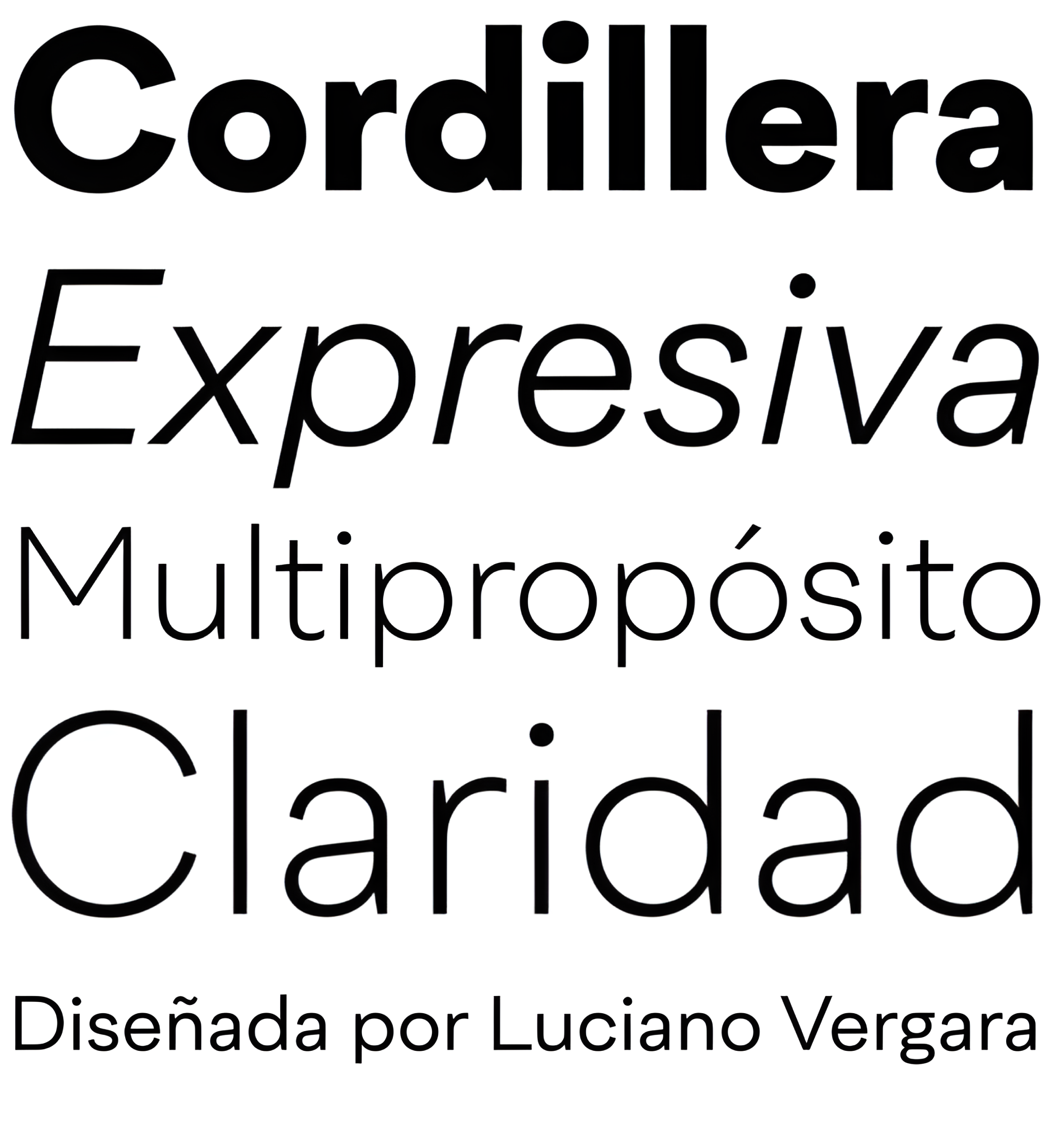
Cordillera
| Descripción | Clara, sencilla y polivalente. Presentamos Cordillera, una nueva sans serif diseñada para uso corporativo, que mezcla proporciones clásicas, caracteres geométricos y neogrotescos. |